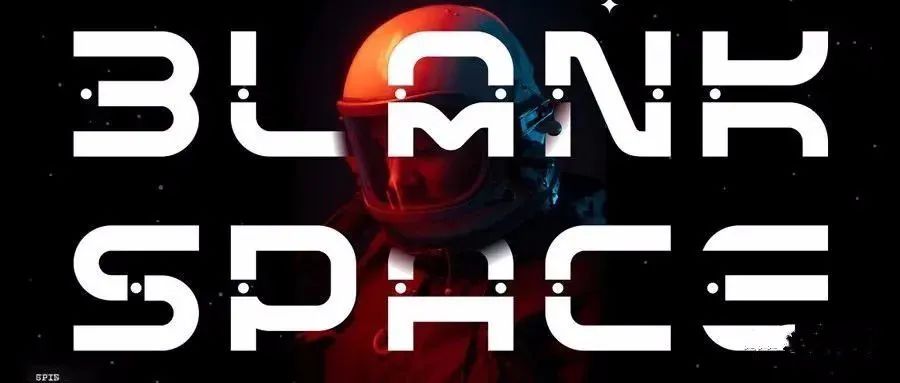
美到窒息的潮流艺术英文字体合集【760期】
潮流艺术英文字体合集非常具有设计感喜欢文字变形设计的看完肯定立马收藏赠送查字体版权网站01赛博朋克科幻机械艺术字体
02蒸汽波风优雅文艺半衬线字体
03新电源设计美学无衬线字体
04千禧年复古风海报标题粗体
05清新现代无衬线字体
06独特互锁圆形专辑插图字体
07趣味嘻哈风涂鸦手绘卡通字体
08酸性菱形弯曲科技感显示屏字体